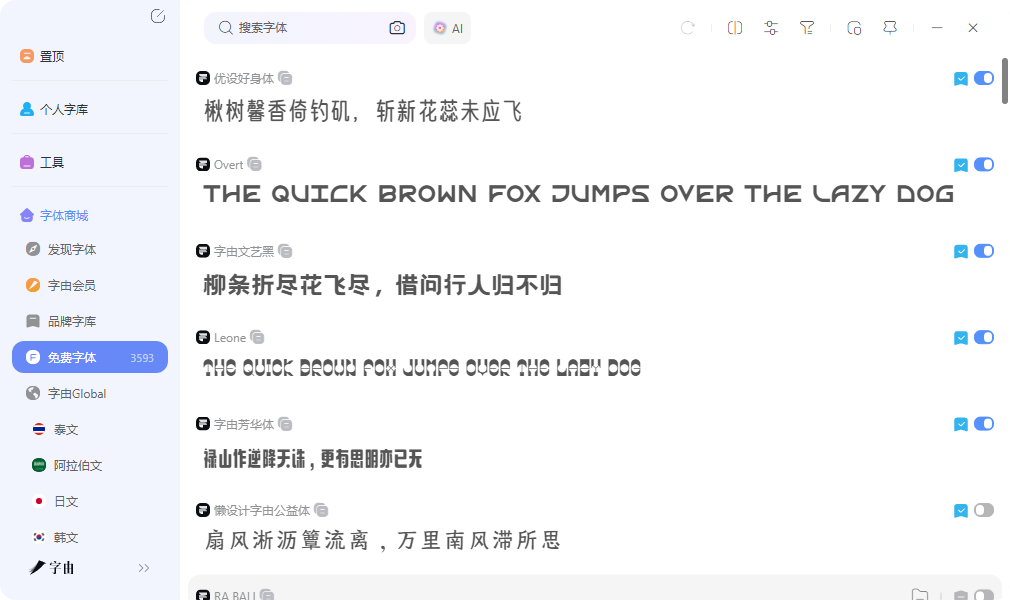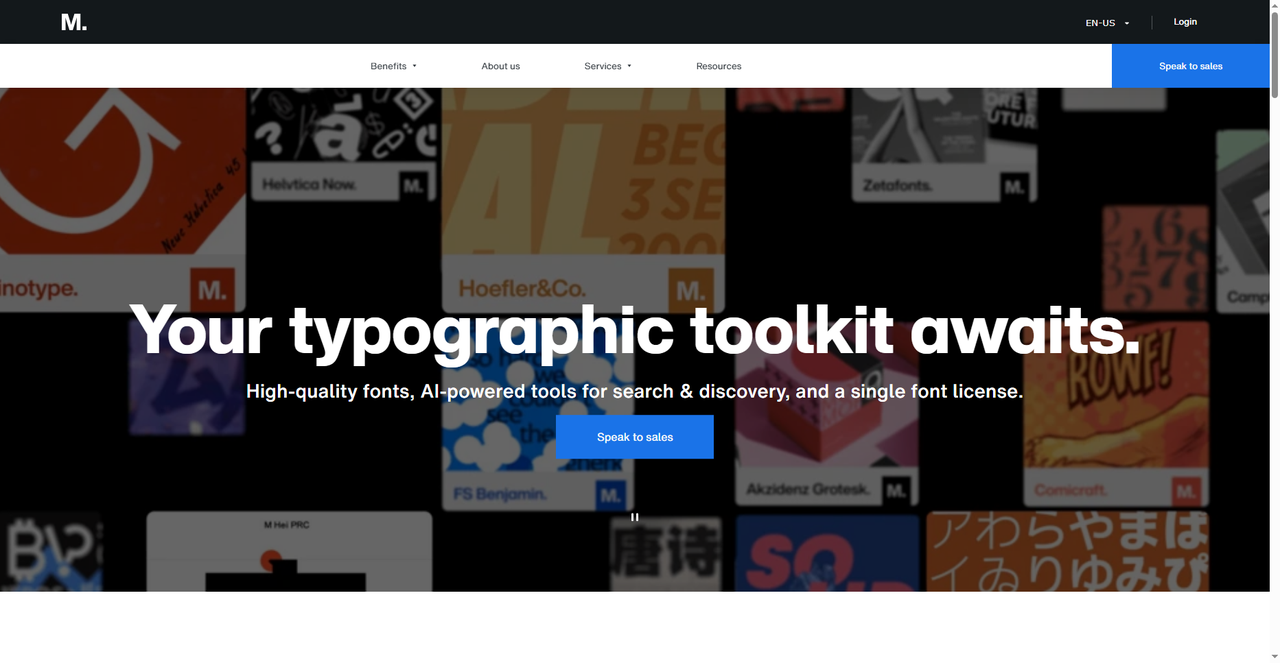
字体库免费商用字体,设计师做项目放心用
接到一个新项目,打开字体文件夹才发现,里面存的文件有些是从论坛下载的,有些是从网盘转的,还有些根本记不得来源。这种场景很多设计师都遇到过。与其在版权问题上提心吊胆,不如一开始就找字体库免费商用资源明确的平台。这篇文章整理了几个靠谱渠道,授权清晰,做项目时能放心用。
字由在解决商用授权这个问题上做得非常好,对设计师来说也十分友好。除了平台收录的字体超过一万款,字由标注字体库免费商用的就超过三千款,这个数量对日常设计来说绰绰有余。每款字体的详情页都清楚显示了授权信息,免费商用标签一眼就能看见,不需要你再去翻说明文件或者搜论坛帖子确认。
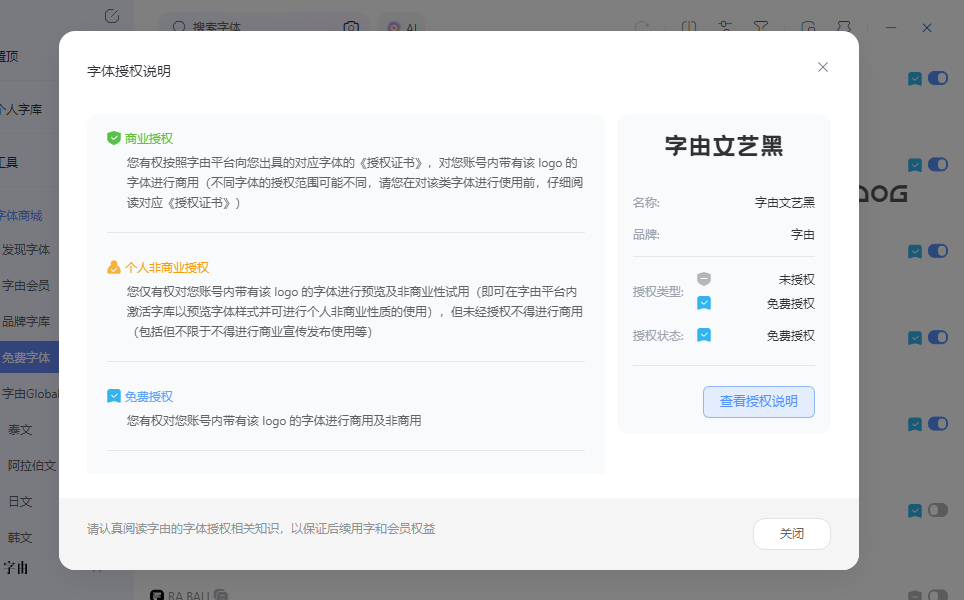
我自己做项目时的习惯是,先勾选免费商用标签,再按风格筛选。要做海报就点进创意或者文艺分类,做PPT就选商务或者现代,做文创项目就选手写或者中国风。这样筛选出来的结果,每一款都能直接用于商业项目,不用担心后续纠纷。优设标题黑、仓耳渔阳体、鸿雷板书简体这些常用字体都在免费商用列表里,覆盖了标题、正文、装饰等多种需求。
一键激活的功能配合商用筛选特别顺手。在传统流程里,你要先确认一款字体能商用,再去下载安装,装完还要重启软件才能用。字由把这个过程压缩成点一下激活按钮,字体立刻出现在 PS、AI、PPT 里,而且授权信息已经确认过了。跨设备同步也很实用,你在公司整理的免费商用字体分组,回家登录同一个账号全部都在。这种把"找字体、确认授权、安装使用"三件事打包解决的方式,是我推荐字由作为主力字体库免费渠道的主要原因。
2、Monotype
Monotype 是全球知名的大型字体平台,首页展示了 Helvetica Now、FS Benjamin 等经典字体家族。平台的特色在于提供 AI 驱动的字体搜索和发现工具,以及统一的字体授权许可方案。对于需要高质量商业字体的企业用户来说,Monotype 的资源覆盖面和专业度都很可观。平台提供的单一授权模式简化了版权管理,一款授权覆盖多种使用场景。这里的字体以付费精品为主,但质量和独特性通常比免费资源更高,适合对字体品质有严格要求、预算充足的品牌项目。如果你需要为字体库免费之外的补充渠道找一个高质量入口,Monotype 值得考虑。平台上的字体家族通常包含多个字重和变体,做完整的品牌 VI 或者多语言排版时,这种完整的字体家族比零散的单款字体更实用。
3、 Awwwards Free Fonts
Awwwards 是设计师都知道的一个权威平台,他们策划的 Free Fonts 合集目前有 289 款字体,全部是免费资源。这个合集的优势在于"精选"二字,不是海量堆砌,而是经过专业筛选的,每一款都有设计品质保证。
页面上的字体涵盖了多种风格,从 Geist Sans、Geist Mono 等现代无衬线体,到一些更具创意的展示字体都有。因为是 Awwwards 背书,这里的字体在网页设计和视觉项目中表现普遍不错。对于需要扩充字体库免费资源、又不想在海量结果里翻找的人来说,这 289 款精选字体是一个很好的起点。每款字体都标注了来源和下载链接,获取方式直接。我偶尔会来这里看看有没有新加入的字体,发现一些平时在其他平台注意不到的好资源。对于做网页设计或者品牌视觉的人来说,这里的字体风格比较契合现代设计趋势。
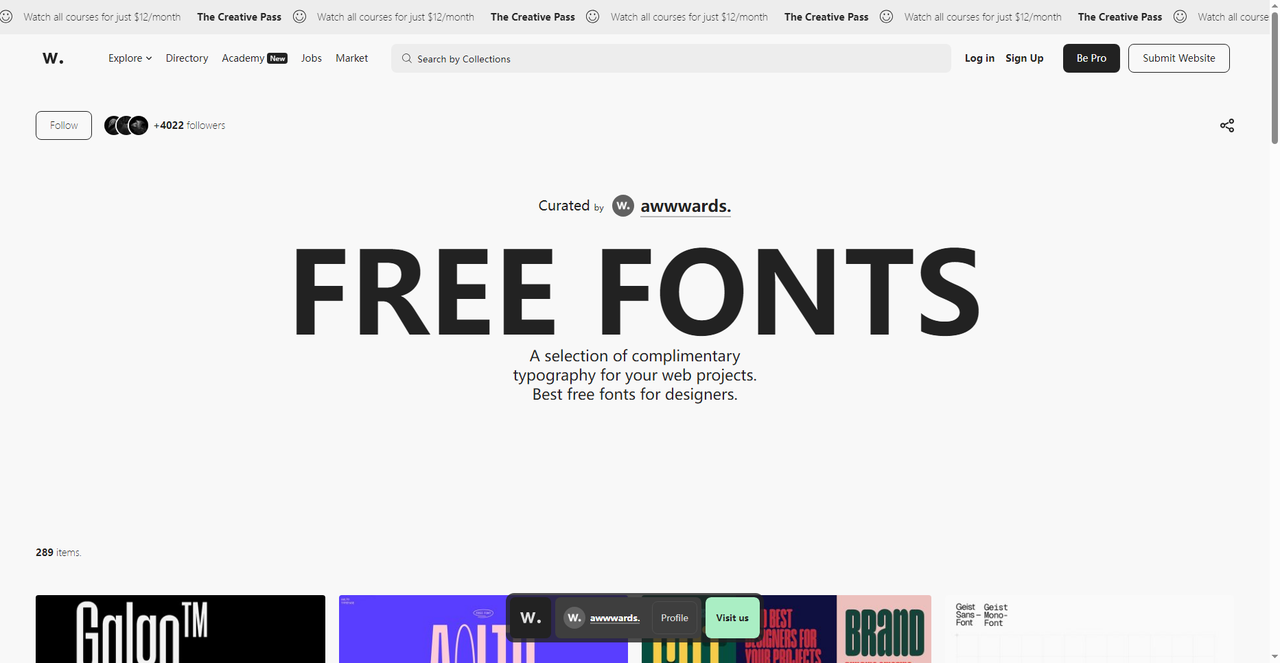
4、DaFont Handwritten
DaFont 是一个老牌的免费字体下载平台,Handwritten 分类下目前收录了超过 805 款手写字体。Bigtimes、Brittany Signature、Sweetest Cat Ever 等热门字体都有很高的下载量,说明 community 对这些字体的认可度不错。
平台的优势是资源量巨大、分类极其细致。除了 Handwritten,还有 Fancy、Script、Calligraphy、Brush、Retro 等几十个分类,几乎涵盖了所有你能想到的风格。每款字体都标注了下载次数、作者信息和授权说明,部分免费商用,部分仅限个人使用,下载前记得确认一下。对于需要大量手写风格字体库免费资源的用户来说,DaFont 的分类体系和资源量是主要的吸引力。我自己找英文手写体的时候经常会来这里逛,按热度排序后前面的字体基本不会踩雷。不过要注意授权类型有不同,有些需要捐赠作者才能获得商用权,下载前仔细看说明。
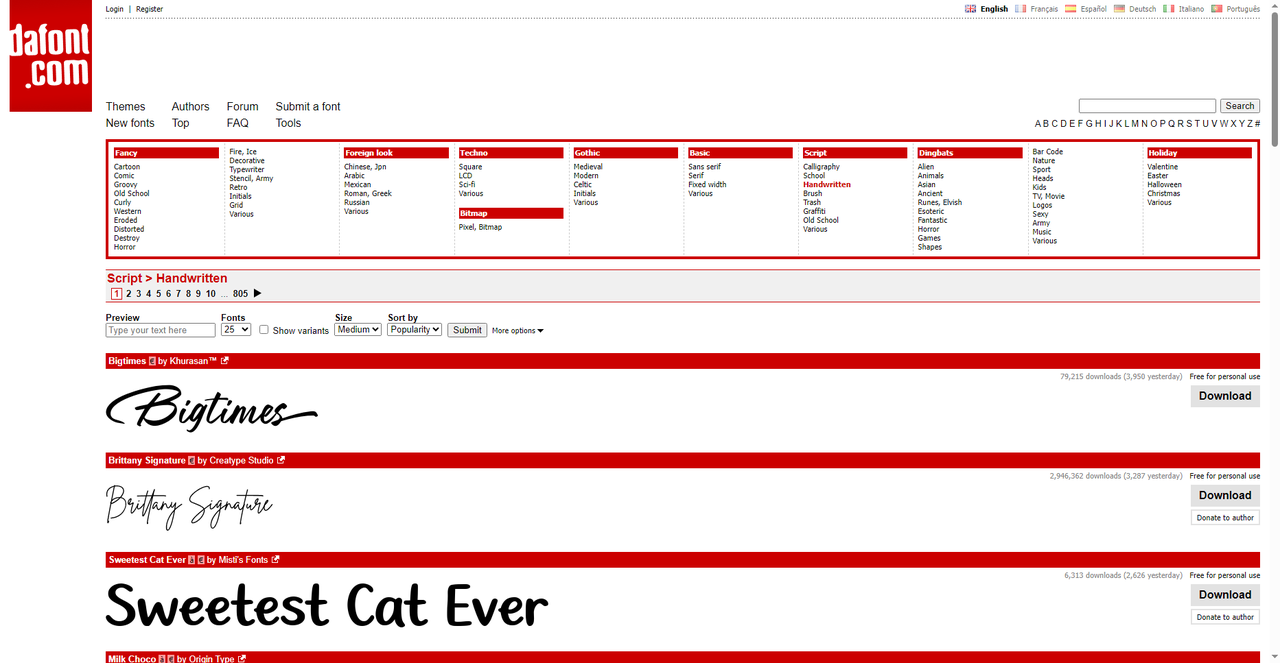
5、FFonts
FFonts 是一个专注免费字体的下载平台,左侧导航按 Regular Fonts、Retro Fonts、Rock Fonts、Round Fonts、Sans Serif Fonts、Sci-Fi Fonts、Script Fonts、Serif Fonts 等做了详细分类,每个分类都标注了收录数量。Sans Serif Fonts 有 8158 款,Script Fonts 有 7224 款,资源量很可观。
每款字体都有详细的参数展示,包括字符数、下载量、是否免费、是否支持 Web Font 等。预览功能支持调整字号、背景色、文字内容,输入自己的文案后实时看到效果,这个细节对判断字体在实际项目中的表现很有帮助。对于需要精确筛选、不喜欢在海量结果里翻找的用户来说,FFonts 的参数化展示比较高效。如果你正在搭建一套字体库免费资源,从这里批量下载一些基础款字体,按分类整理好,是一个快速扩充库存的方式。
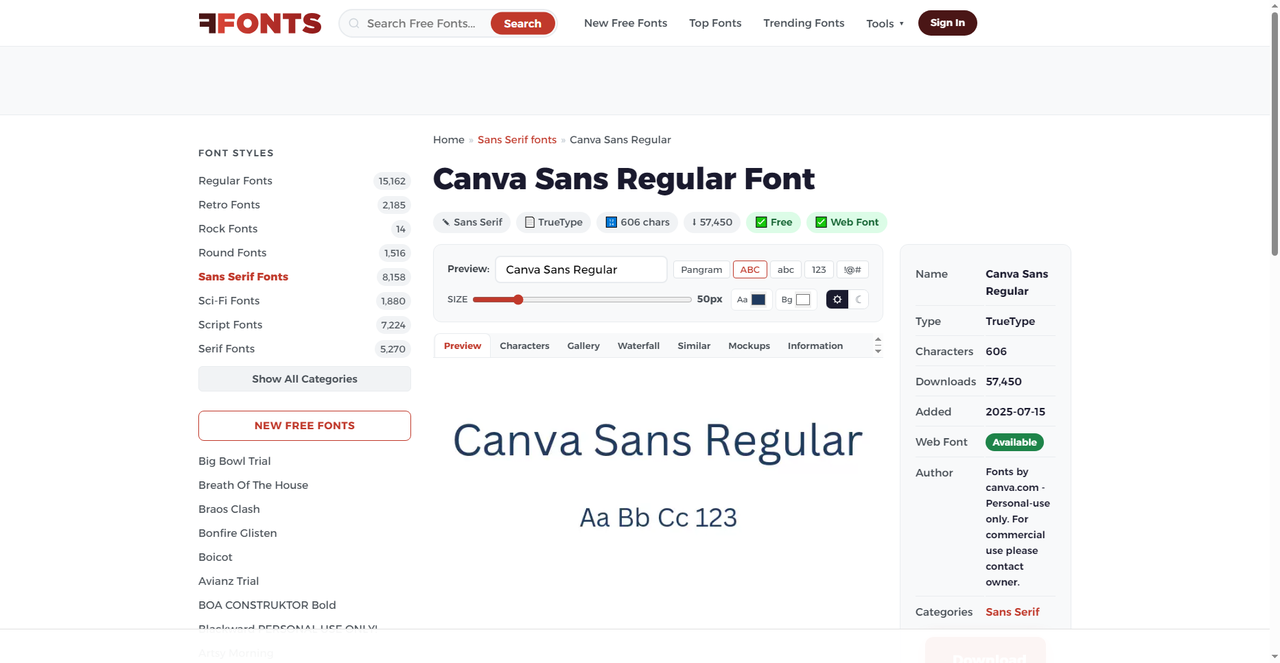
做商业项目怕踩版权坑,字由的免费商用标签和一键激活是最让人放心的组合,中文资源全、授权清晰、跨设备同步,作为主力字体库免费渠道特别省心。Monotype 适合预算充足的高端项目。Awwwards 的 289 款精选是快速找到好字体的捷径。DaFont 和 FFonts 资源量大、分类细,适合英文免费字体的批量搜集。几个平台搭配着用,商用字体这块基本就不愁了。